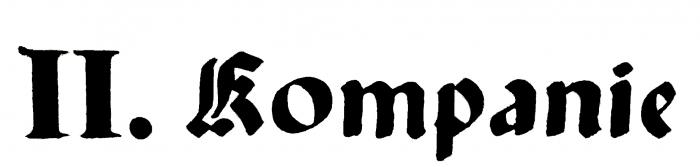
Schriftart gesucht (II. Kompagnie)
ich möchte gerne wissen, um welche Schriftart es sich hier handelt.
Vielen Dank im vorraus unter den Frakturen habe ich das K nicht finden können.
Gelöst von dtom
Auf die Schnelle hab ich hier eines gefunden. Der Schriftzug sieht aber sehr weichgespült aus …
Dass das hangeschrieben ist, sieht man ja deutlich. Es gibt aber sicher eine ähnliche Schriftart, die von mir oben verlinkte kommt ja von der Grundgestalt schon halbwegs gut hin:
Wenn man sich jetzt noch die Serifen weggespült denkt …
Ich glaube gar nicht mal, dass hinter diesem Schriftzug eine Satzschrift stecken könnte. Statt dessen gan es ja, zumeist von den Schreibfeder-Herstellern herausgegeben Schreiblehrbücher, welche dann zumeist ebenfalls von Kalligrafen geschribene Muster-Alfabete enthielten. die dann nur im generellen Schriftstill, also Schwabacher, Frakturschrift, Unziale Gotische- und Neugotische Schrift usw bezeichnet warren, wonei diese dann von Lehrbuch zu Lehrbuch deutlich unterschiedlich gescxhrieben sind- Möglich, dass auch der Schreiber dieses Textes sich an solch ein Buch hielt, und daher die Schrift auch keinen speziellen Namen hat.
z.B. Hefte wie dieses:
In der Tat habe ich das vom T-Shirt abfotografiert und nach Bearbeitung hier eingestellt. (Wurde garantiert mal weichgespült)
Ich habe mich für Paladin FLF entschieden und kann nun weiter machen und dank Euch mit der richtigen Schriftart Angebote für neue
Hemden und Blusen einholen
Klar. Schau Dir mal das kleine o an. Das ist weder eine Fraktur noch eine Gotische/Textura. Das ist eine Schwabacher. Das passt auch zu der ganz leichten Neigung der Buchstaben. Die ähnliche Schriften sind alles Schwabacher mit „modernen“ Großbuchstaben, bei denen Zierelemente (IMHO der neueren Textura) eingeflossen sind. Da kannst Du lange die Frakturschriftmuster durchwühlen ...
Hier gibt es die Paganini ebenfalls und hier (bestimmt sicher, da hat catfonts ja sein Pfötchen drauf) sogar eine UNZ1-Version, die gleich aussehende PaladinFLF gibt es hier.